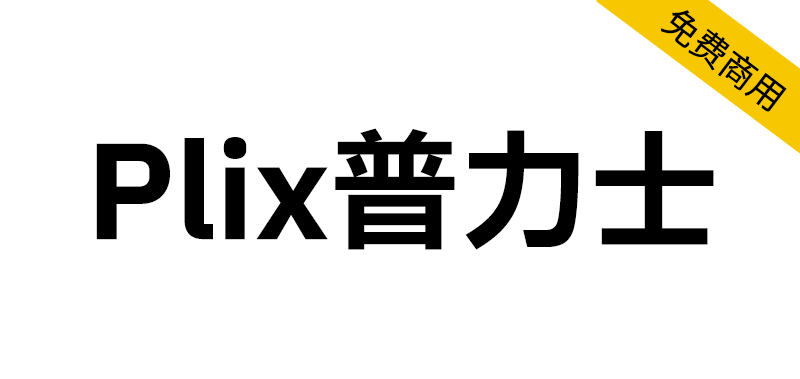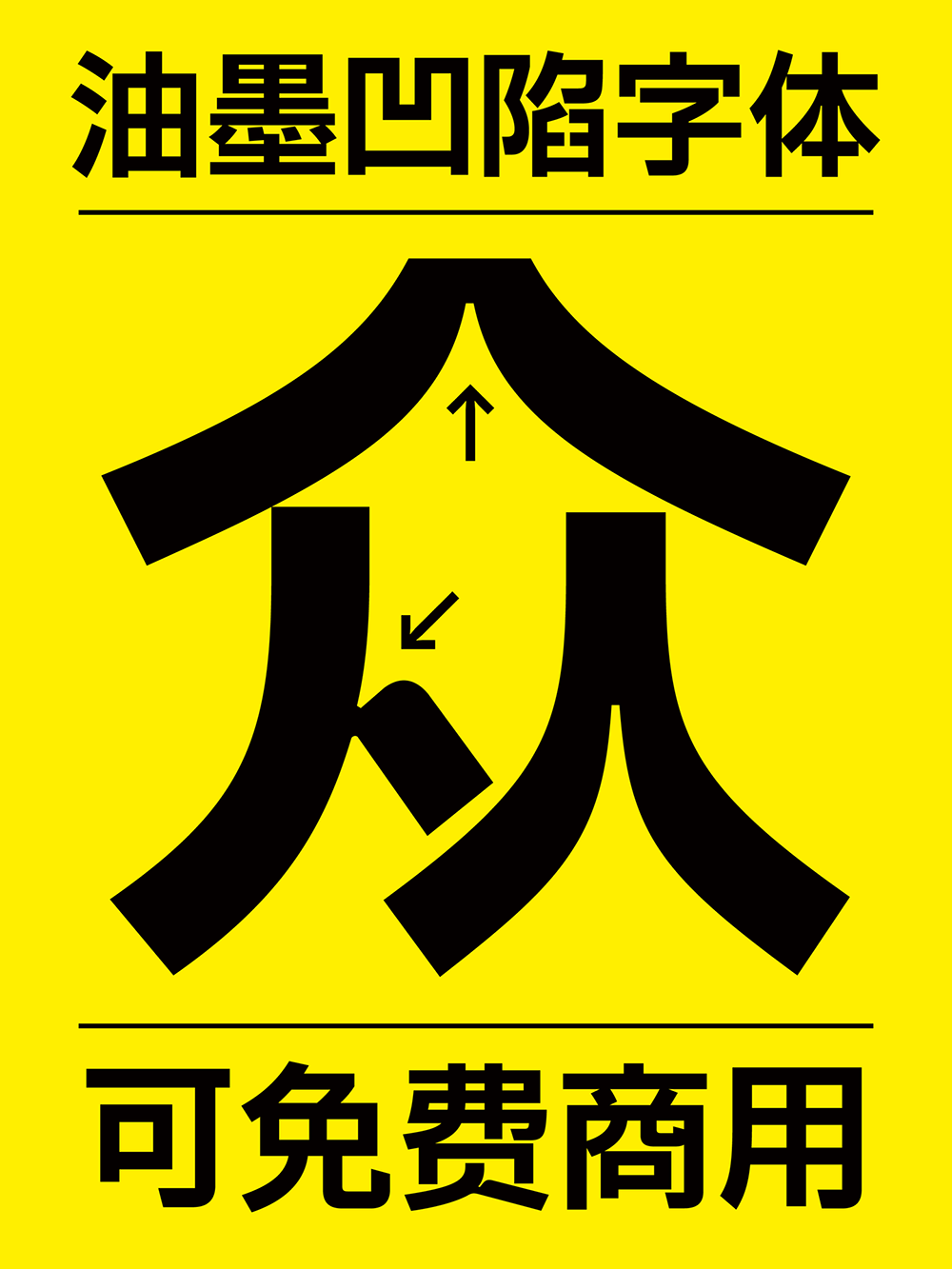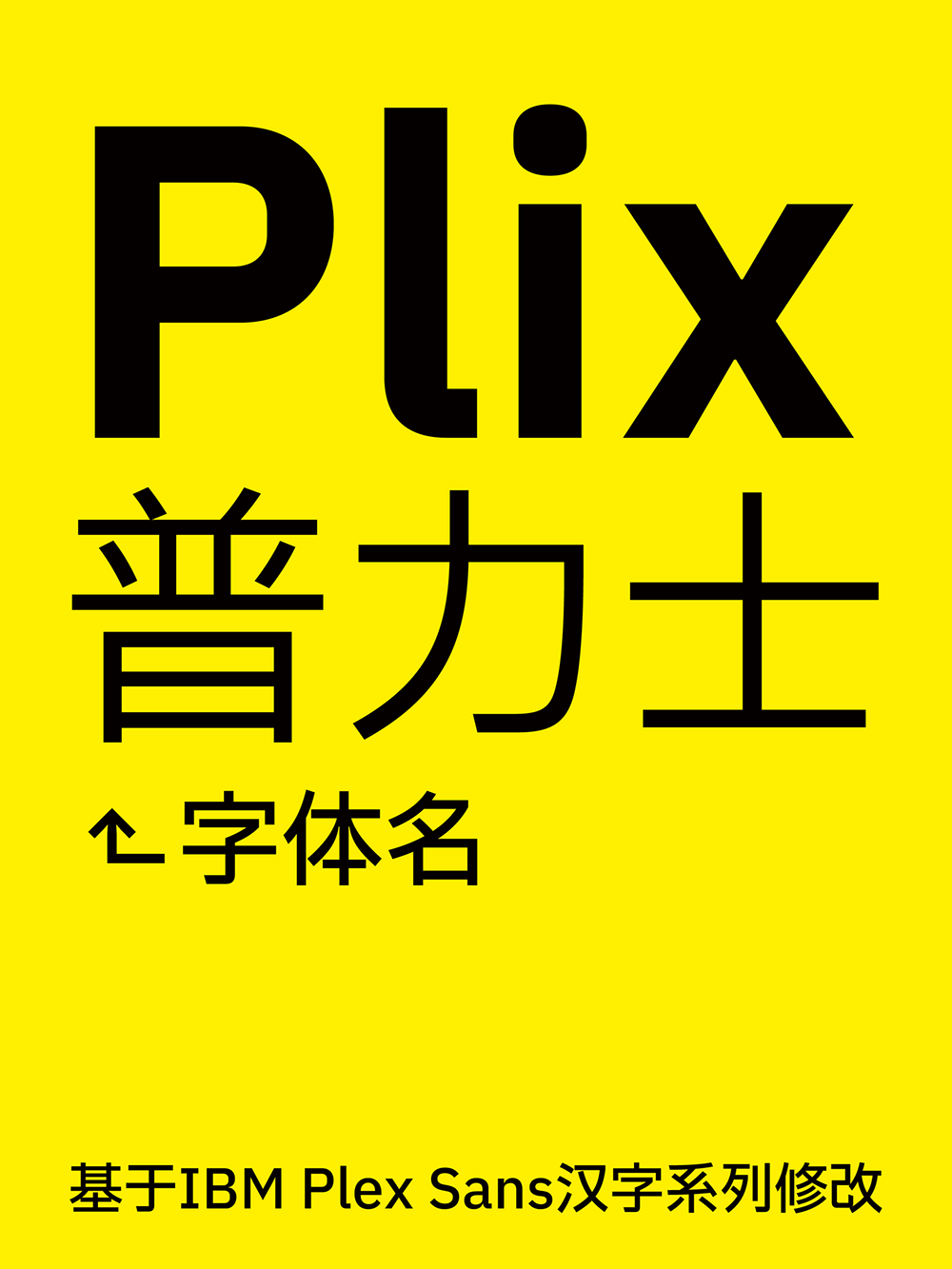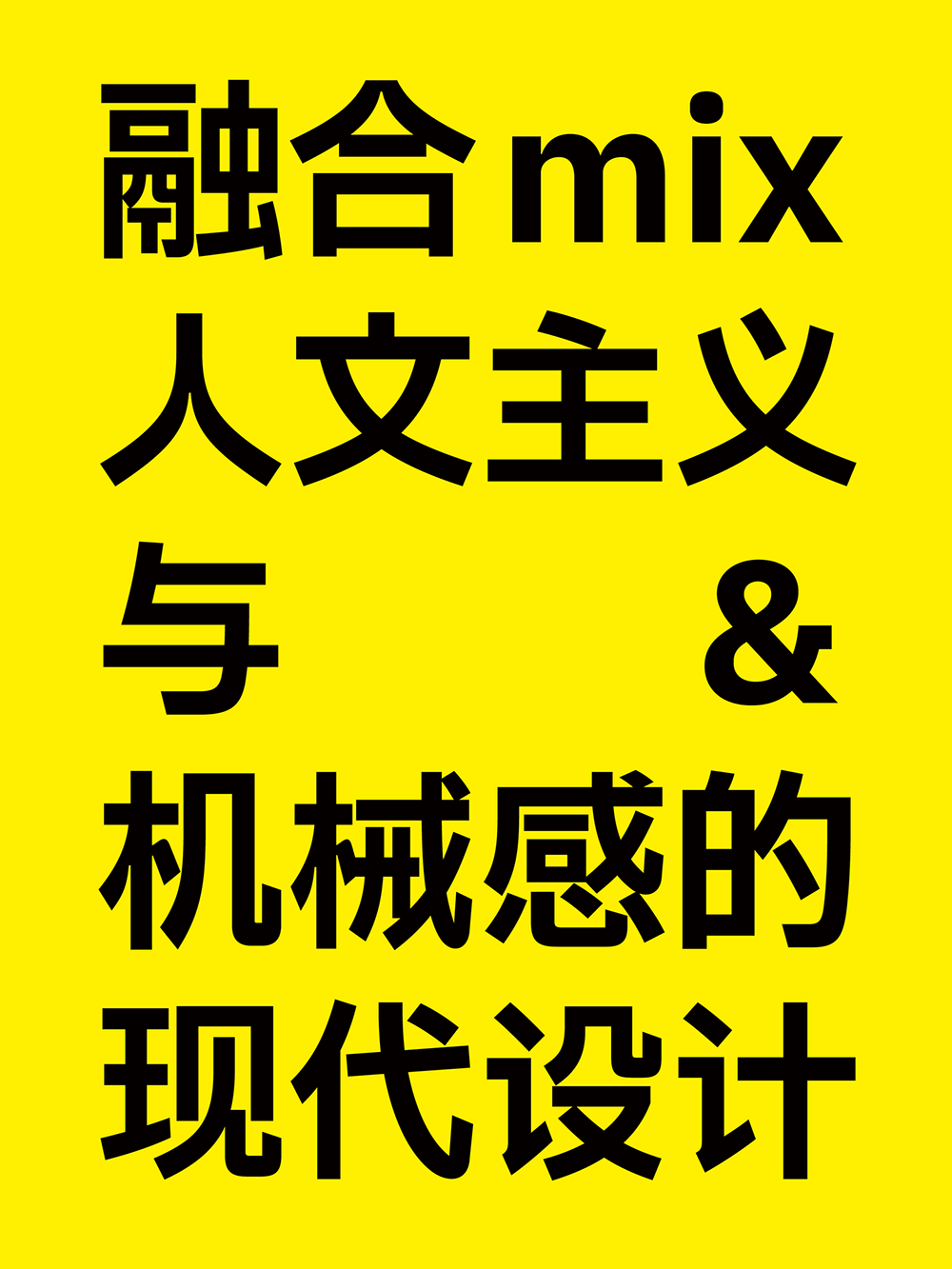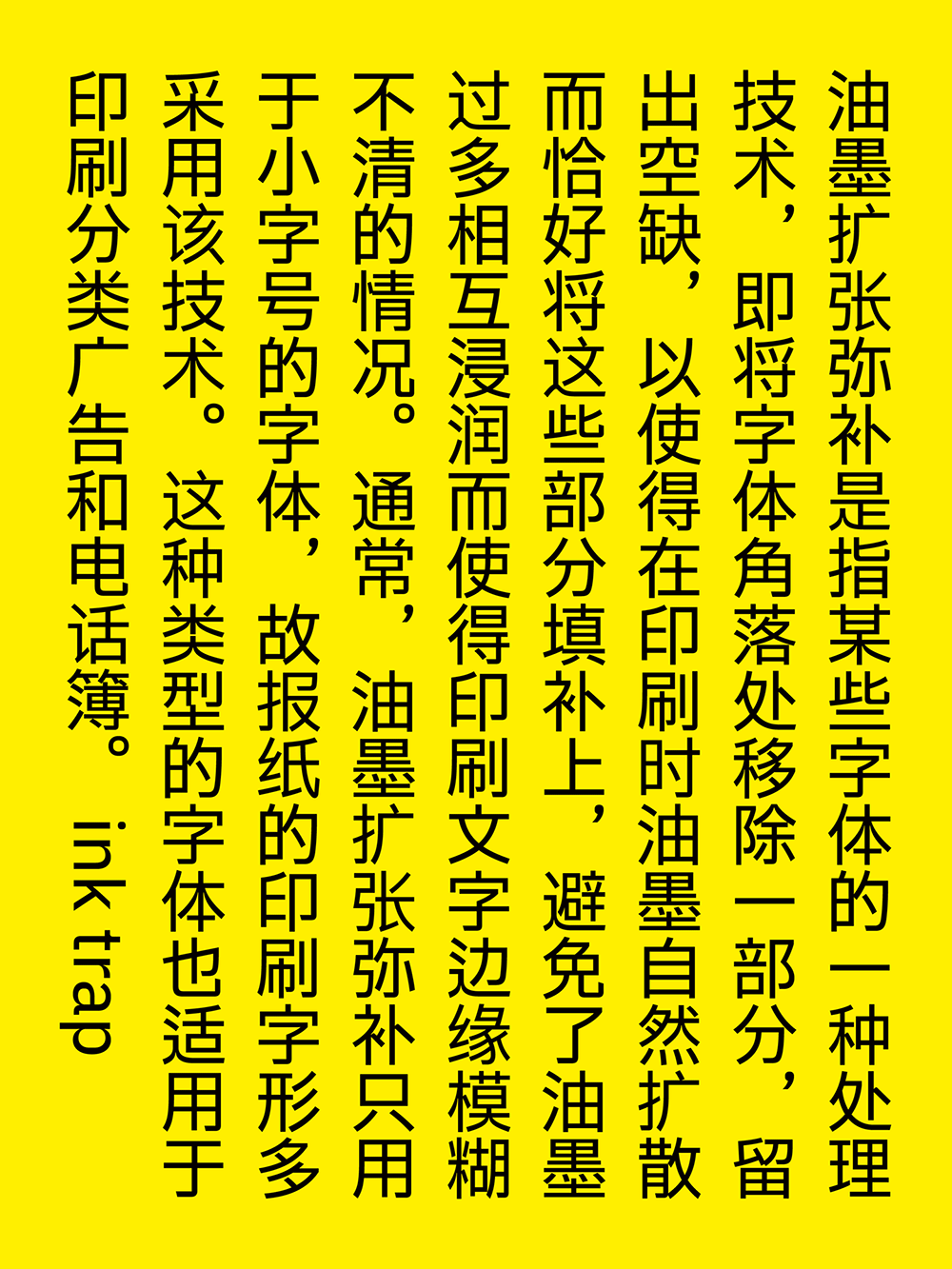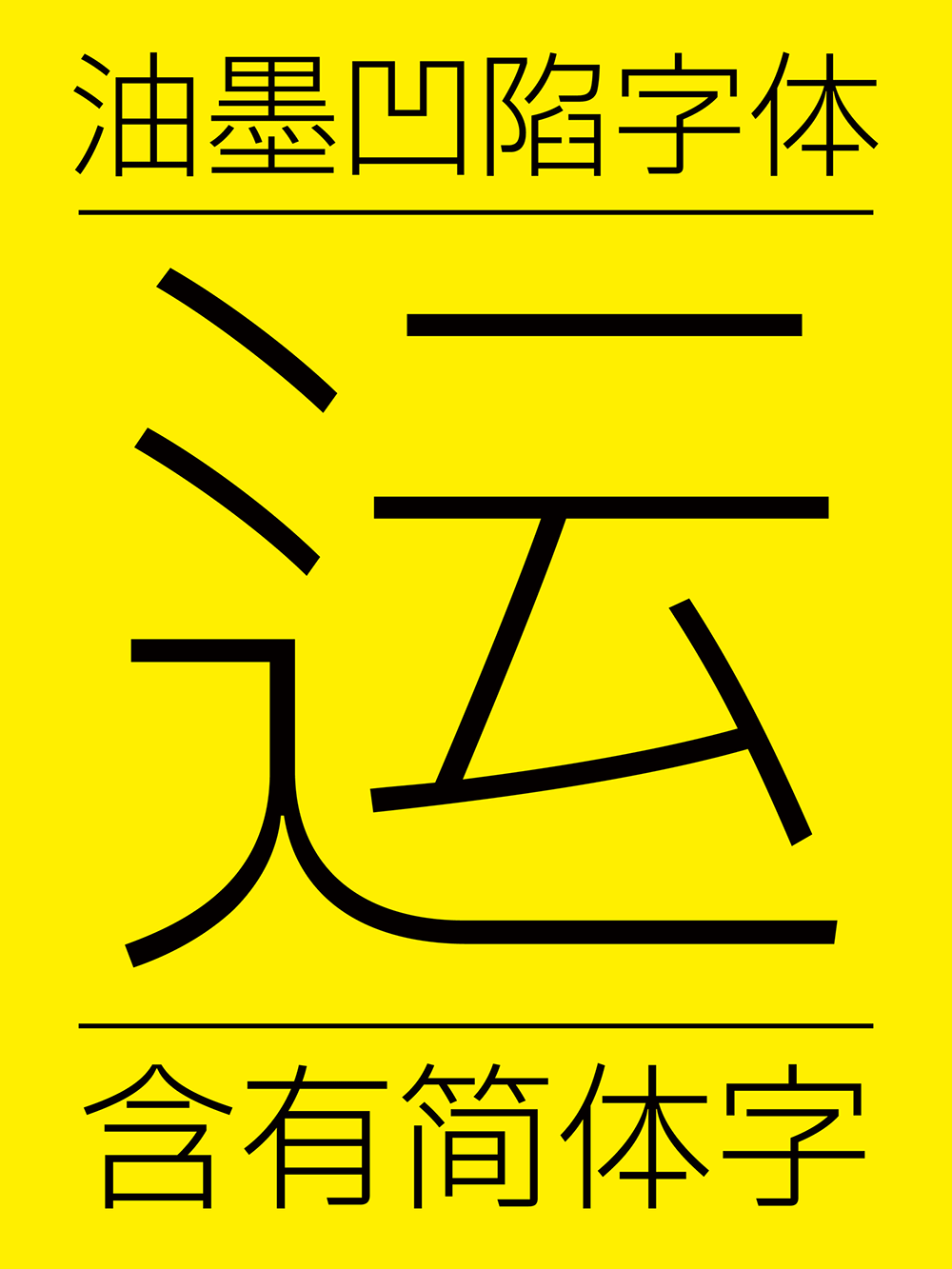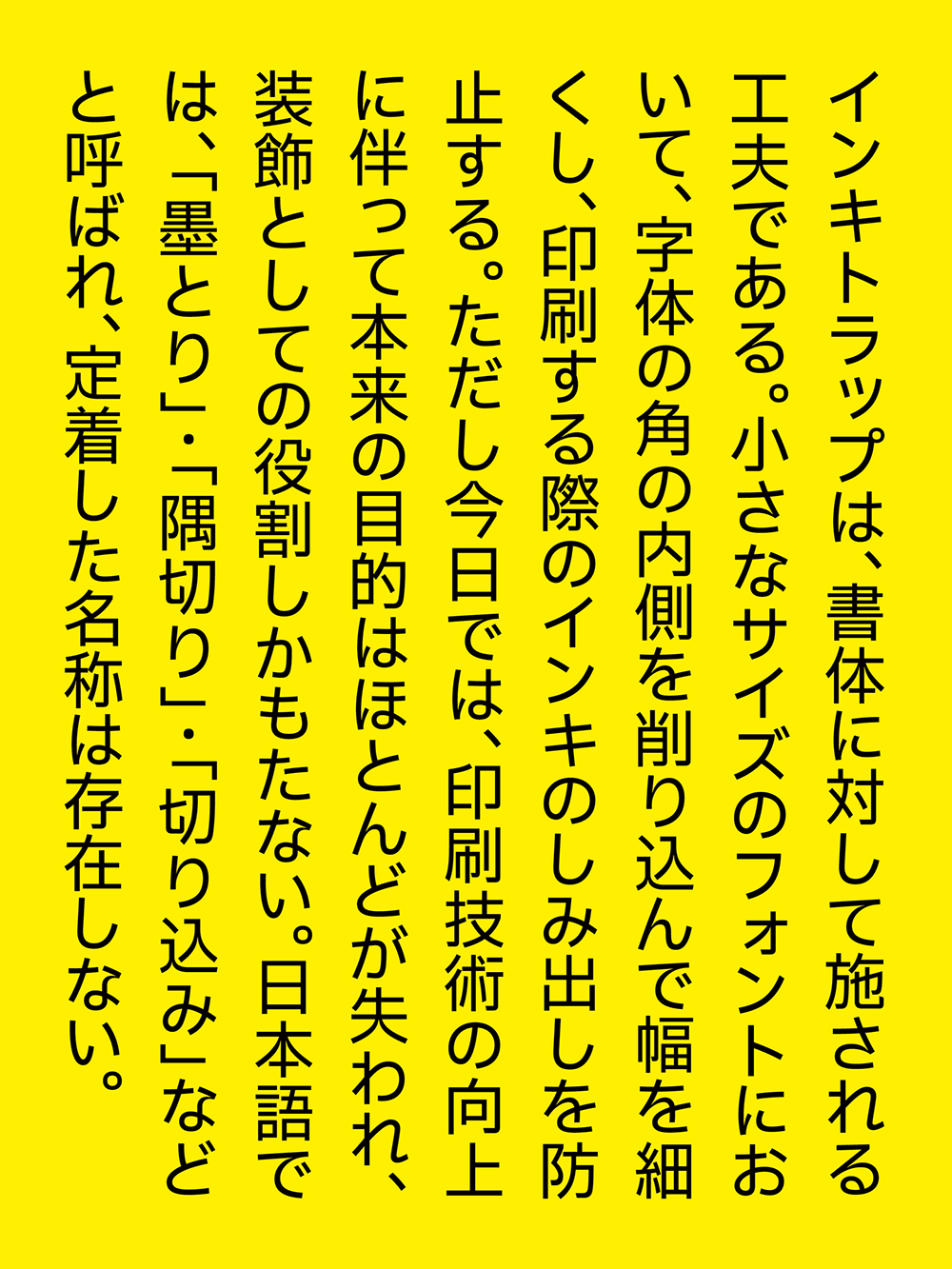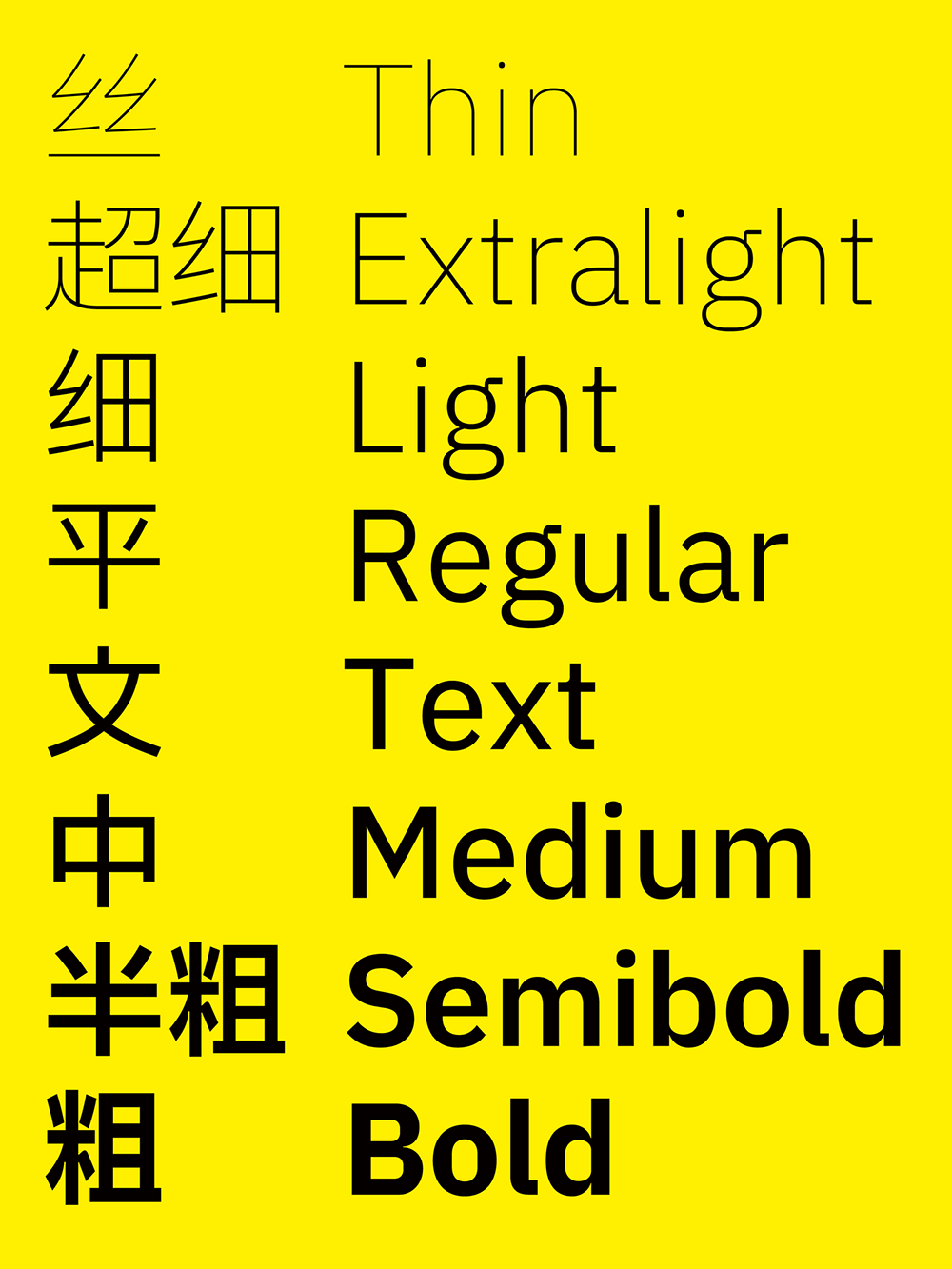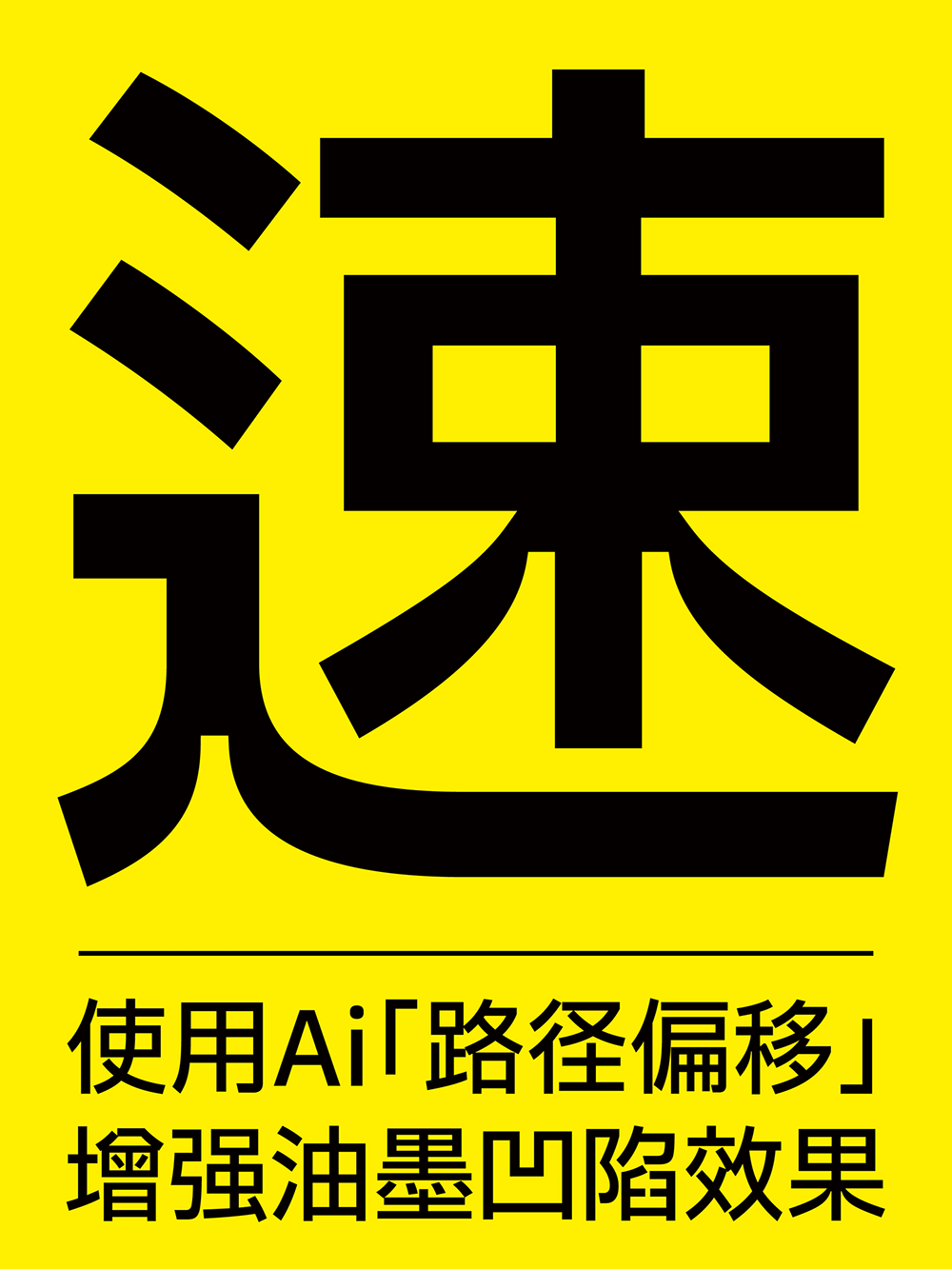
Plix普力士是基于IBM Plex Sans汉字系列的合并字体,可以显示简体字,还可以显示不规范字形的简体字,适用于现代、科幻、未来、电子、潮流艺术场景。
Plix普力士:用JP补上TC,再补上SC。标点居角,日本字形;Blix卜力士(标点居中版):用TC补上JP,再补上SC。标点居中,繁中字形。